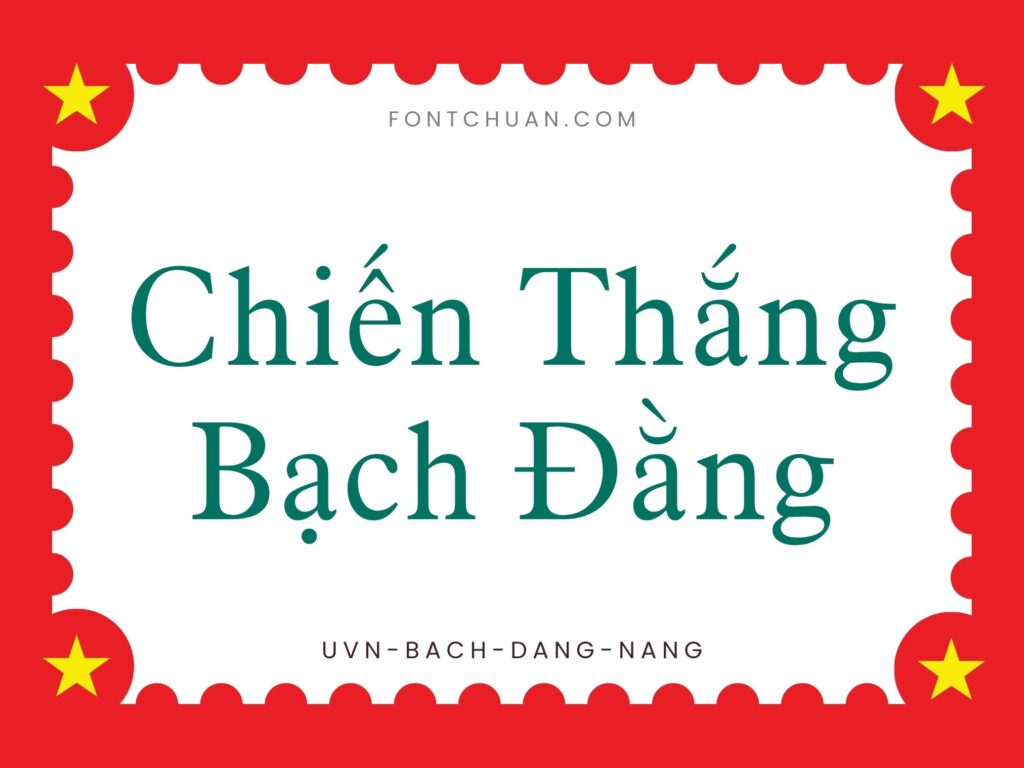
Font UVN Bach Dang Nang Việt Hóa
UVN Bạch Đằng là một kiểu chữ đậm nét, thể hiện cá tính mạnh mẽ và bản sắc Việt Nam thông qua thiết kế cứng cáp và gợi cảm hứng truyền thống. Nằm trong bộ sưu tập font UVN, font Bạch Đằng mang tinh thần của lịch sử và văn hóa, rất thích hợp với các dự án cần tạo dấu ấn đặc biệt hoặc truyền tải cảm giác trang trọng, tự hào dân tộc. Font này chỉ được sưu tầm và đăng bởi thành viên của Font Chuẩn nhằm mang đến cho cộng đồng thiết kế thêm một lựa chọn chất lượng, phù hợp trong nhiều ngữ cảnh sáng tạo tại Việt Nam.
Với thiết kế serif mạnh mẽ, các đường nét của UVN Bạch Đằng được nhấn nhá rõ ràng, độ dày đều và tạo độ tương phản cao giữa các nét chính và nét phụ. Kiểu chữ này hoạt động hiệu quả trên tiêu đề, poster, bìa sách, biển hiệu, hoặc các dự án mang tính văn hóa – lịch sử. UVN Bạch Đằng đặc biệt phù hợp trong các ngành như quảng cáo, giáo dục, bất động sản và công nghệ, đồng thời có thể ứng dụng tốt trong các sự kiện như Tết, lễ hội, ngày Nhà giáo và các chương trình truyền thống.